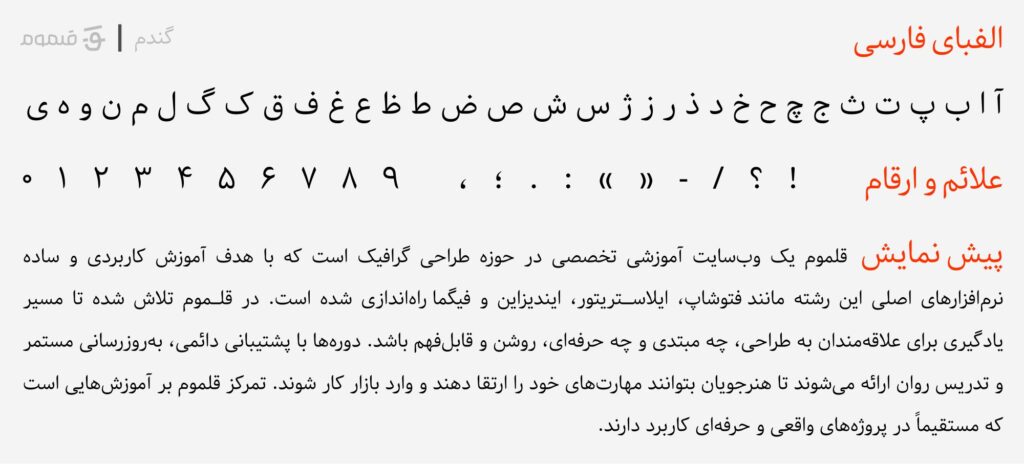
فونت گندم با حالوهوای دستنوشته و دوستانه، انتخابی جذاب برای پروژههایی است که نیاز به حس طبیعی و غیررسمی دارند. این فونت بیشتر در طراحیهای گرافیکی، پوسترها و شبکههای اجتماعی کاربرد دارد و برای متنهای طولانی چندان مناسب نیست.
گندم یک فونت آزاد و رایگان است و اگر به دنبال ایجاد حس گرما و صمیمیت در طراحیهای خود هستید، میتواند گزینهای بسیار خوب باشد.